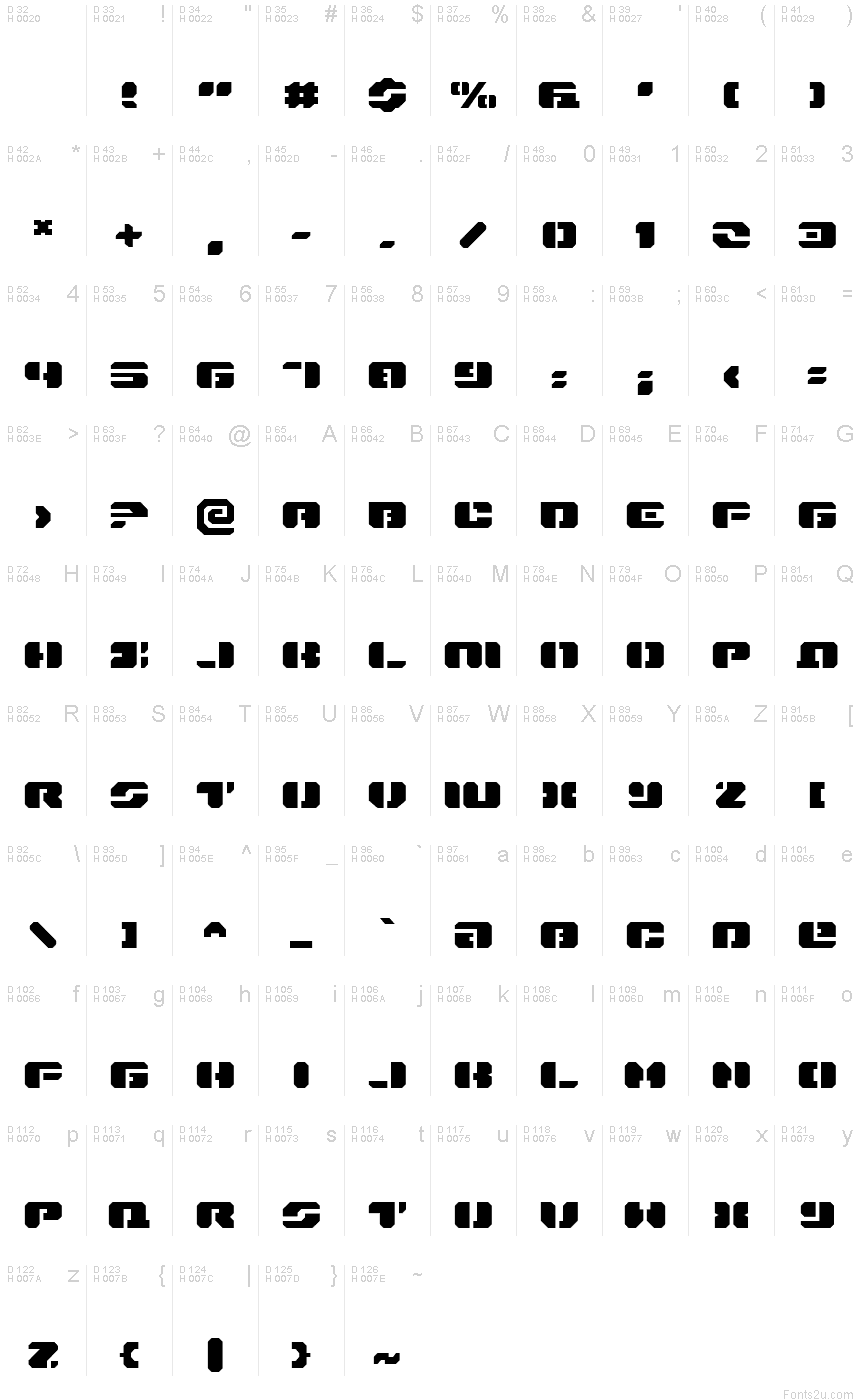
Dan Stargate Extra-Expanded è un font display futuristico gratuito di Iconian Fonts, caratterizzato da proporzioni ampie e una geometria dai tagli netti. Tratti segmentati e curve squadrate conferiscono alle lettere l'aspetto tipico delle scritte su astronavi o di un pannello di controllo digitale.
Le sue forme larghe e interrotte creano un ritmo tecnologico di grande impatto, perfetto per loghi di videogame e titoli di film di fantascienza. Utilizzate questo font gratuito per poster di eventi, copertine di album, grafiche di interfacce o progetti tecnologici dove caratteri angolari che richiamano macchinari, schermi e ambienti industriali sono fondamentali, senza bisogno di fronzoli.